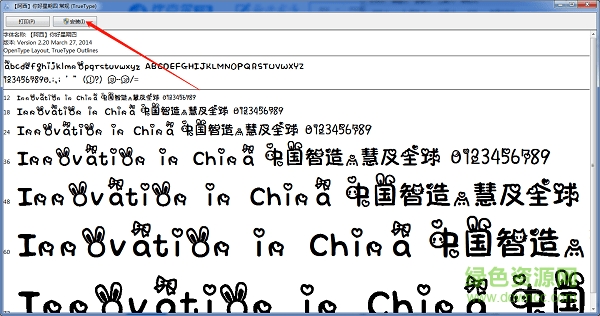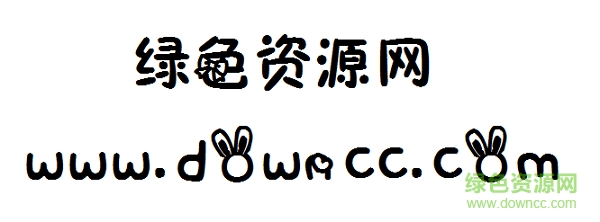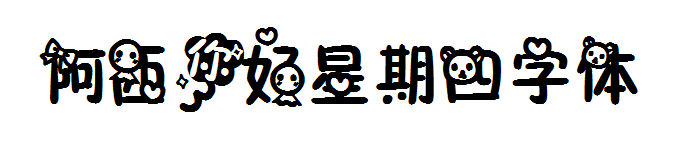
你好星期四字體
阿西你好星期四字體是一款非常呆萌的字體,字體中添加了超多的可愛小元素,小手掌、小兔子及小愛心等等,超級滿足你的少女心,非常適用于各類設(shè)計作品,喜歡就來綠色資源網(wǎng)下載體驗吧!
阿西你好星期四字體簡介:
阿西你好星期四字體是一款超級可愛的卡通字體,這款字體在小寫英文字母、標點符號、數(shù)字以及漢字的視覺效果上會有很不小的改變,會把它們掛上可愛的掛飾,比如說兔子耳朵、愛心、貓咪、蝴蝶結(jié)等等,非常的可愛哦!